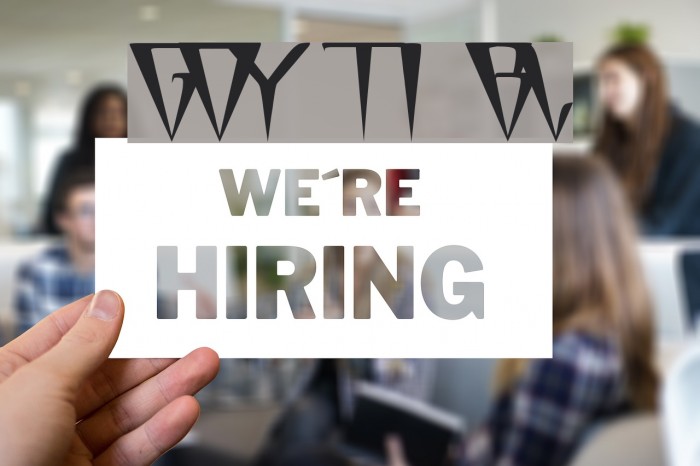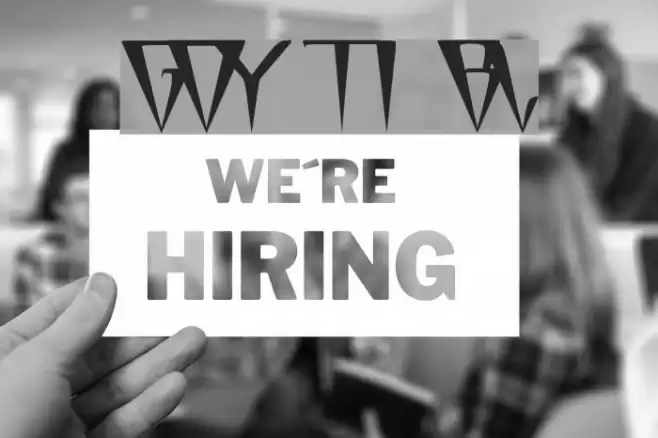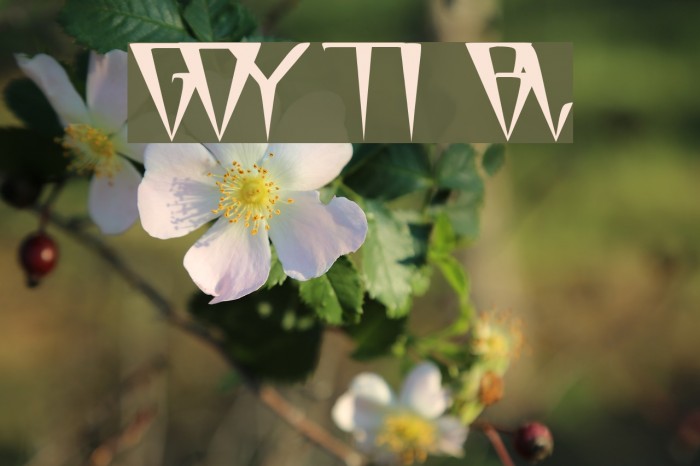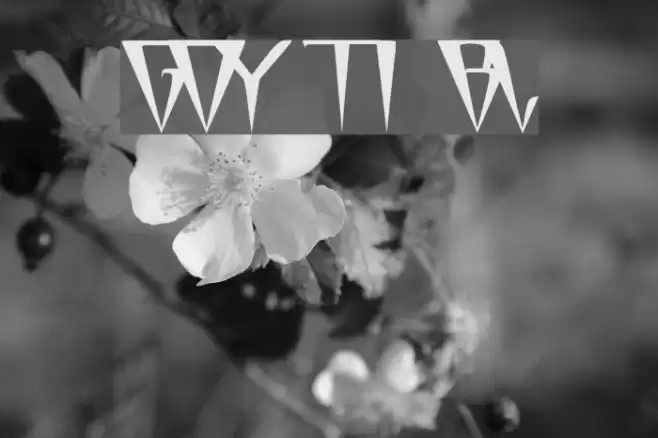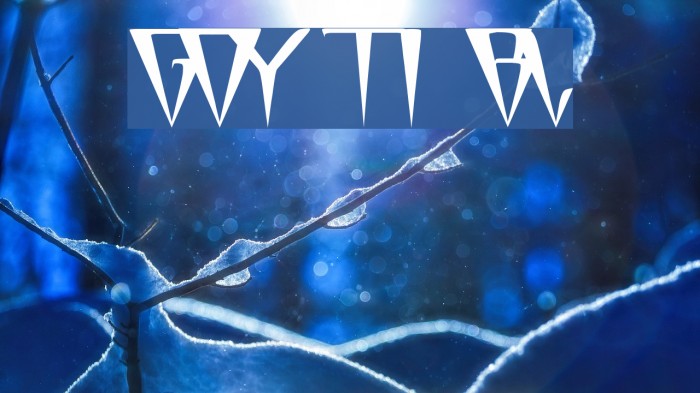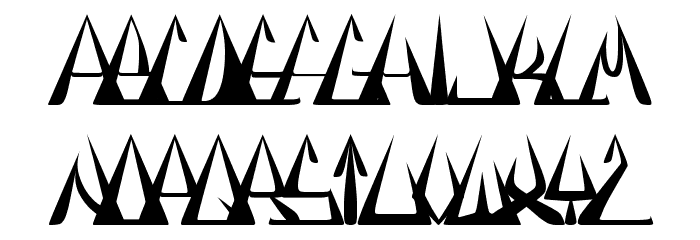
GlOrY ThIn BoLd Font
GLORY-THIN-BOLD Litere mari
GLORY-THIN-BOLD Litere mici
GLORY-THIN-BOLD Alte caractere
| Nume | GlOrY ThIn BoLd |
| Proiecte propuse | Ideal for use in branding, posters, album covers, and any design that requires a bold, eye-catching typeface. |